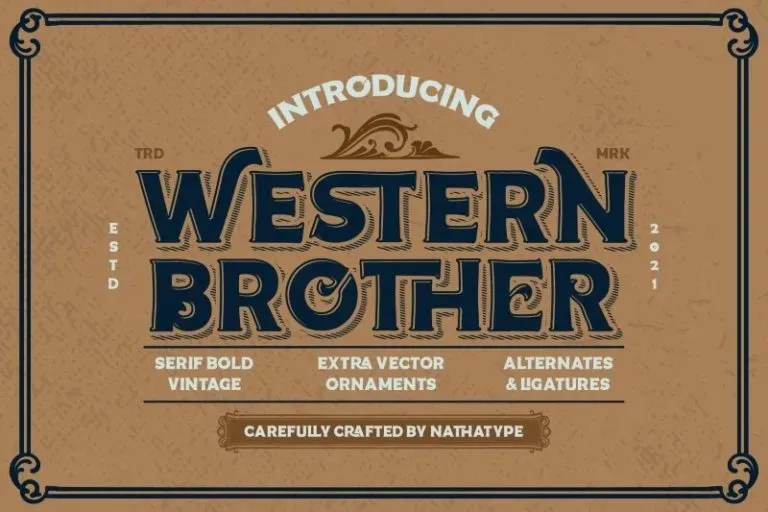
A Western Brother Font é uma opção ideal para quem busca uma mistura de elegância vintage com modernidade vibrante. Inspirada na serifas retro, esta fonte traz alternativas estilizadas que permitem criar design retro e psychedelic sem perder a essência clássica. Perfeito para projetos de identidade visual como logotipos, capas de livros, postais e materiais promocionais, ou até mesmo para personalizar camisetas de esportes. Com seu estilo artístico único, essa fonte se adapta a um amplo leque de necessidades. Seja você criando uma marca inovadora, reforçando sua identidade visual ou apenas dando vida às suas ideias através de uma capa de livro única e imersiva, a Western Brother Font tem o que você precisa para dar um toque retro e divertido aos seus trabalhos.